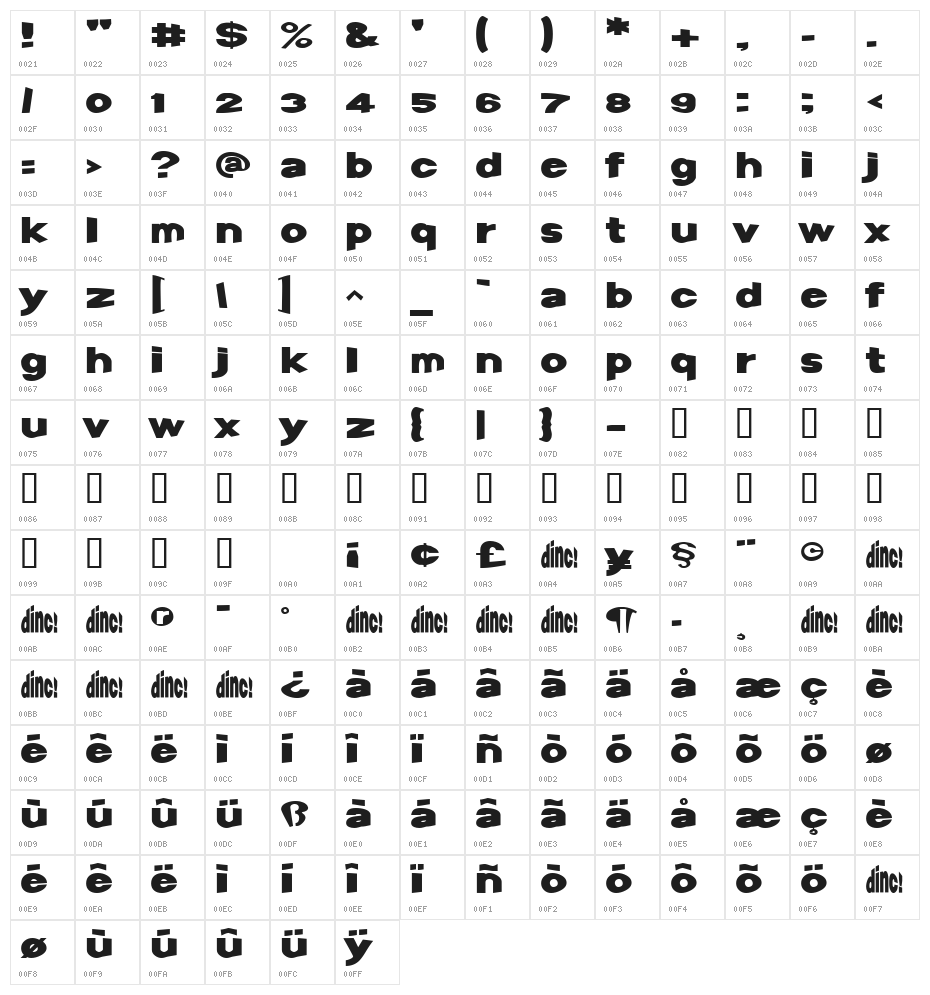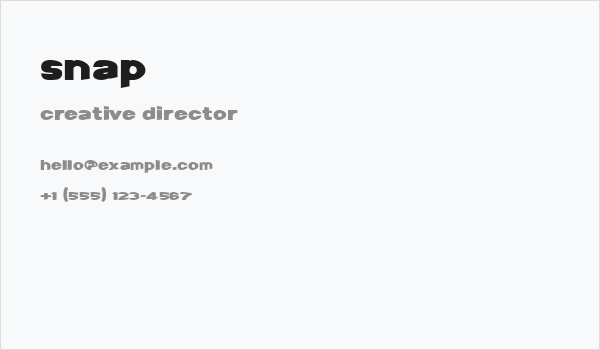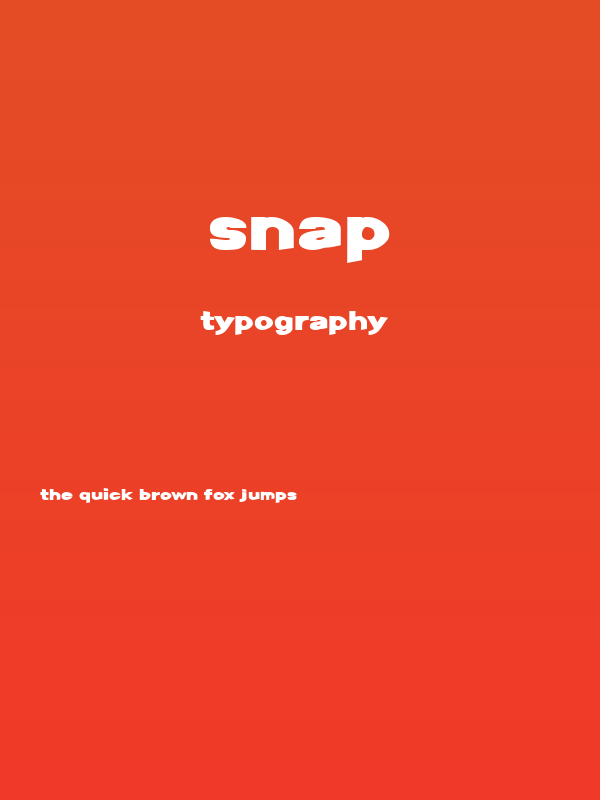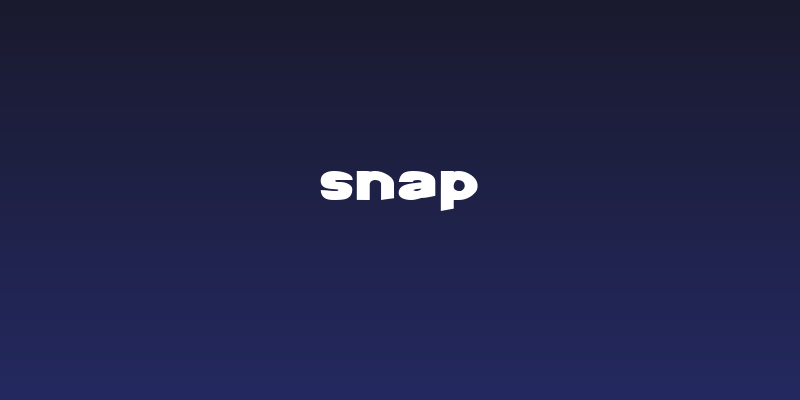
Snap Font
| Stil general | Playful, Energetic |
| Proiecte propuse | Children's books, playful branding, eye-catching headlines, posters, and advertisements. |